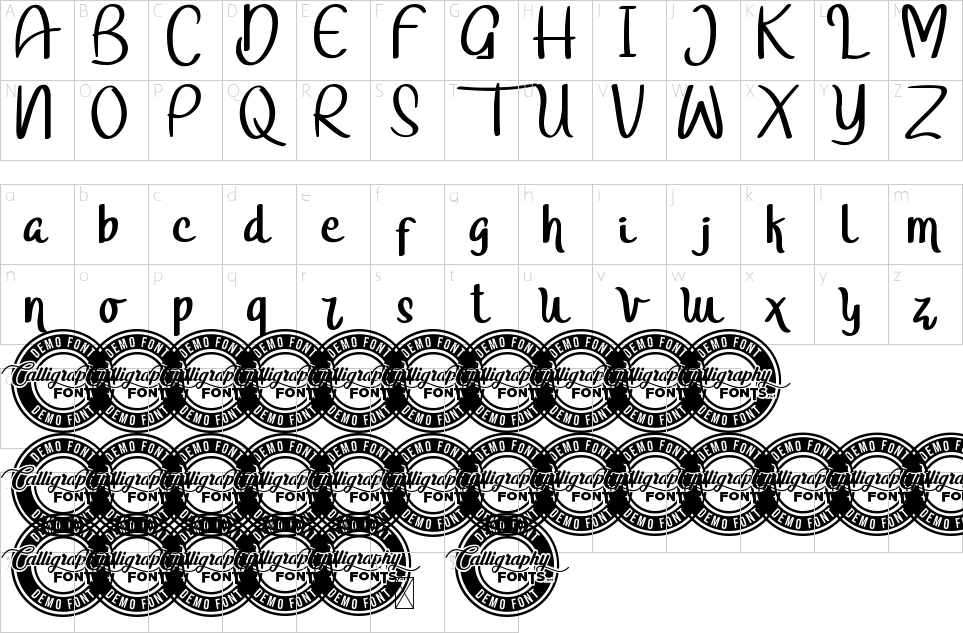
Aproveite a oportunidade de adquirir uma nova e versátil fonte gratuita para seus projetos digitais com Djonathan Font. Desenvolvida pela CalligraphyFonts, essa fonte oferece um equilíbrio perfeito entre elegância e facilidade de uso. Com seu design cuidadosamente criado por especialistas na área da tipografia, Djonathan se tornou uma escolha popular entre designers de gráficos que buscam uma fonte moderna para seus projetos, seja para criação de websites, design de logotipos ou até mesmo para escrita de e-mails pessoais. Com seu download fácil disponível tanto no Windows quanto no Mac, Djonathan está aqui para tornar sua próxima tarefa tipográfica um verdadeiro prazer. Não perca a chance de experimentar o encanto deste belo design.